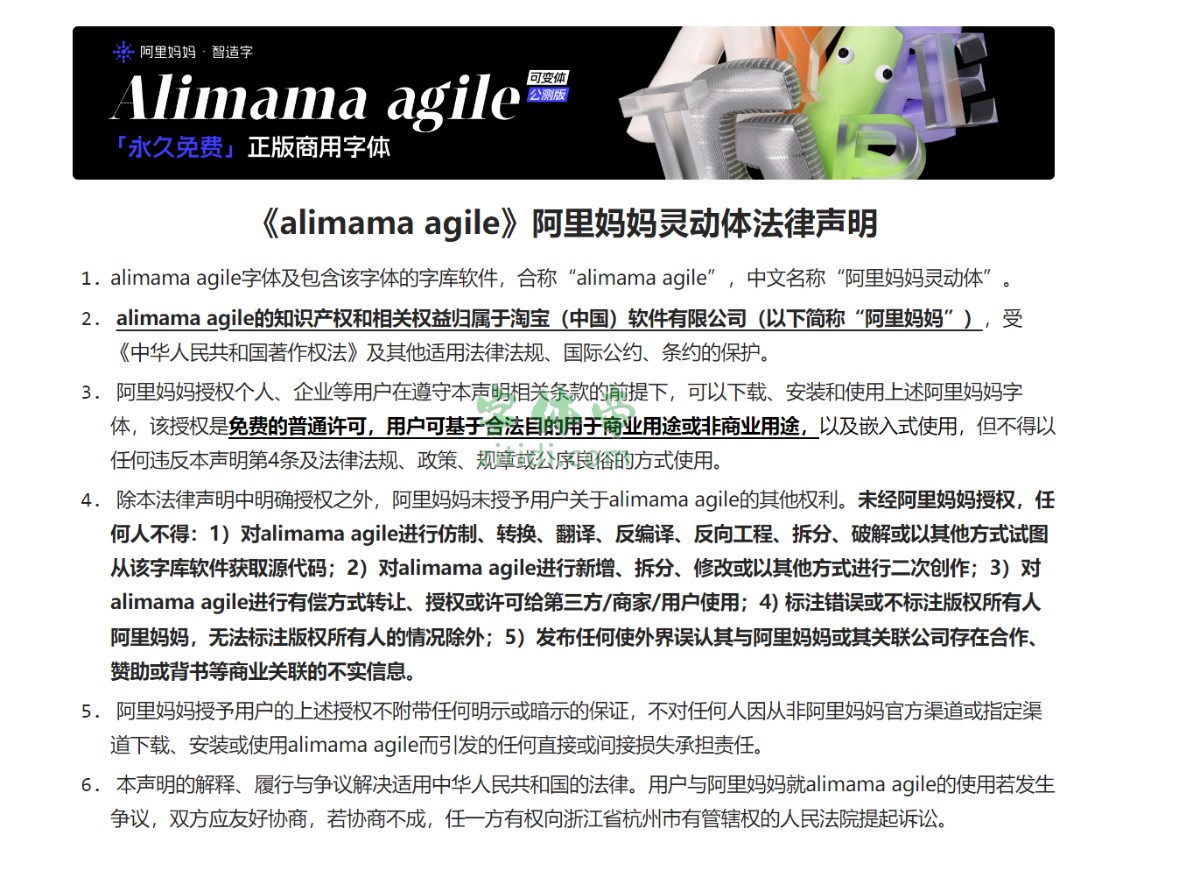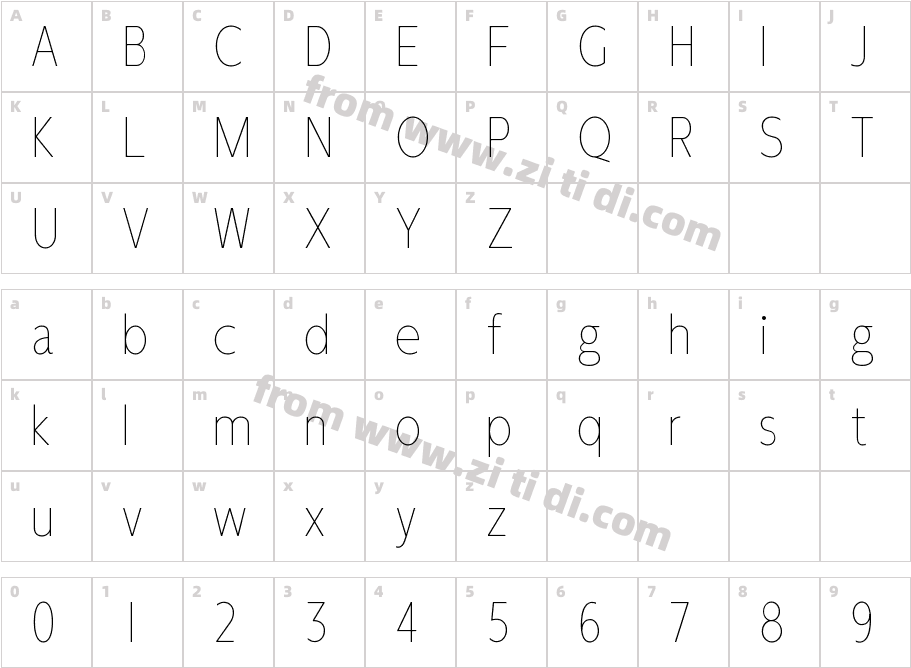
基本信息:阿里妈妈灵动体alimama agile为英文四轴可变字体,收纳的中文字符包括但不限于ASCII,这款字体包含了字重、字宽、倾斜、衬线四款可变方式,英文大小写共52个;常用标点符号共68个,总计120个字符。
设计说明:alimama agile阿里妈妈灵动体是阿里妈妈智造字首次尝试研发的多轴可变的西文字体,4个可变轴(字重、字宽、倾斜、衬线)涵盖非常广阔的使用场景。字重可变让版式中的信息层级可灵活调度,并且赋予各种落地物料微妙的优化;字宽可变带来更灵活的信息编排,让局部文段更适配整体画面;斜体可变使得字体具有凸显强调的特点,增加文本的美感和艺术性;衬线可变让字体从无衬线字无极变化到衬线字, 涵盖西文两大类目,大大满足使用者需求。